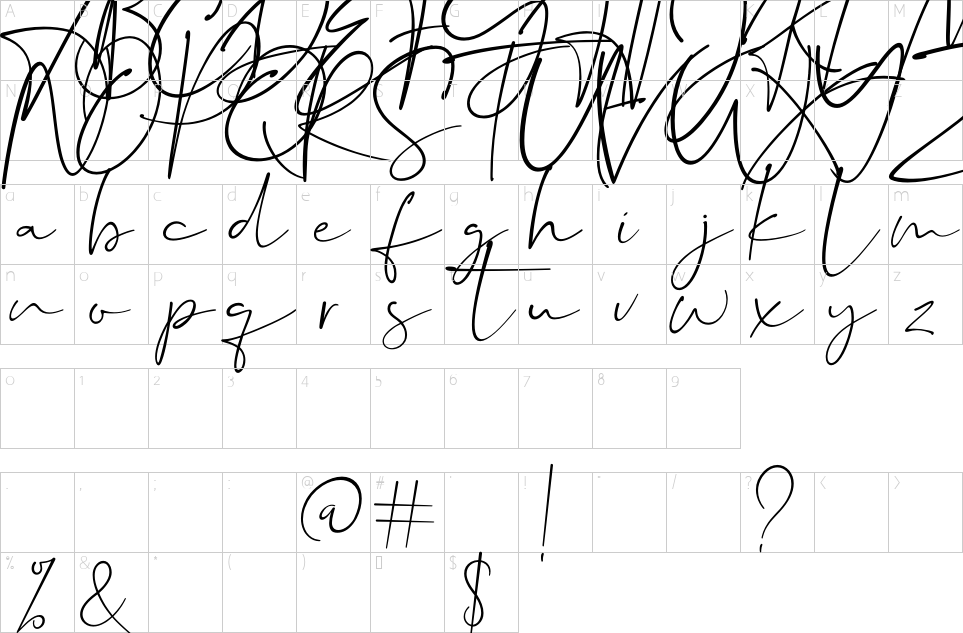
A Dalmatins Font é uma opção gratuita para quem busca estilizar seu design com um estilo elegante e moderno. Ela foi criada pela Sronstudio e está disponível tanto para sistemas Windows quanto Mac, tornando-a útil para diversos ambientes de trabalho. Com 1669 downloads registrados, a Dalmatins vem se destacando como uma opção confiável entre os designers gráficos. Seja você um iniciante ou um profissional experiente, essa fonte oferece a oportunidade de dar vida à sua designação com detalhes sutis e linhas arredondadas que trazem consigo um toque suave e sofisticado. Não perca mais tempo – instale já para experimentar o charme da Dalmatins Font em seus projetos.